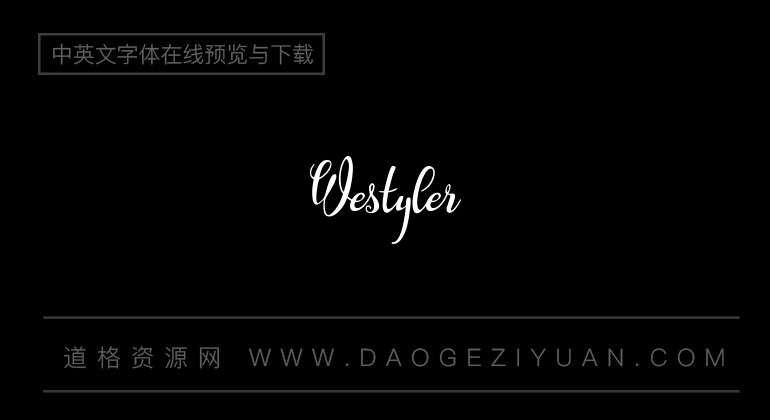
Westyler
Westyler 是一款由西班牙设计师 Angel Koziupa 设计的手写字体,它具有柔和的曲线和流畅的笔画,充满活力和温暖的气息。Westyler 字体的特点是它的简洁性,它的笔画比较细腻,而且它的字体非常容易读取,能够容易让人们理解它的意思。Westyler 字体适用于各种设计项目,可以用于海报、广告、网站设计等等。
Westyler是一款非常不错的手写艺术字体,具有很好的视觉感,适合于文化类的宣传设计、商业类品牌的广告和产品包装设计以及个性化文字排版等较多场景。